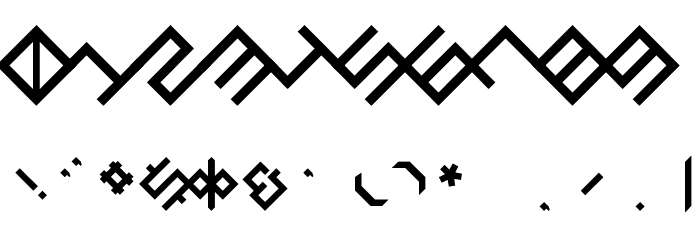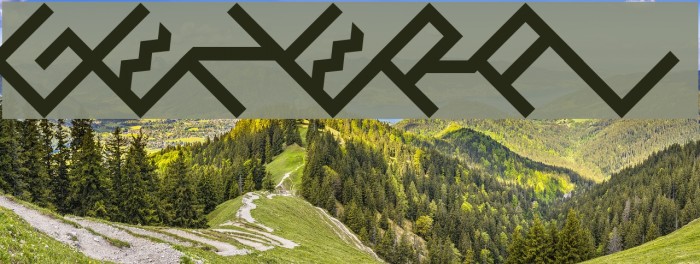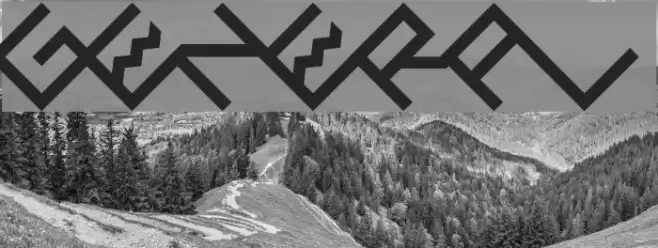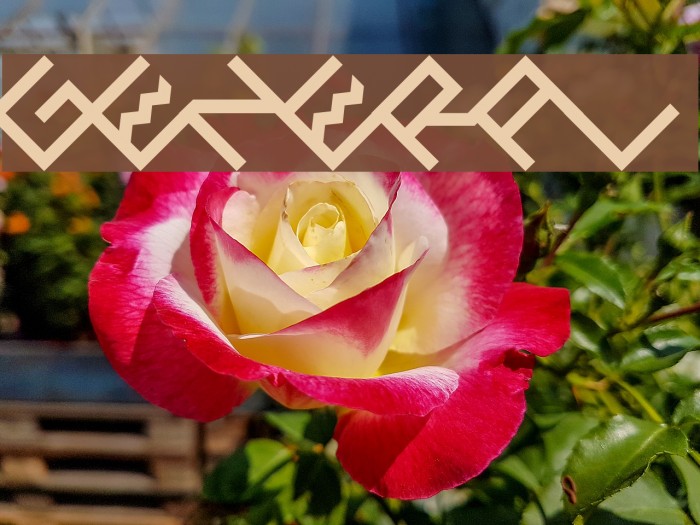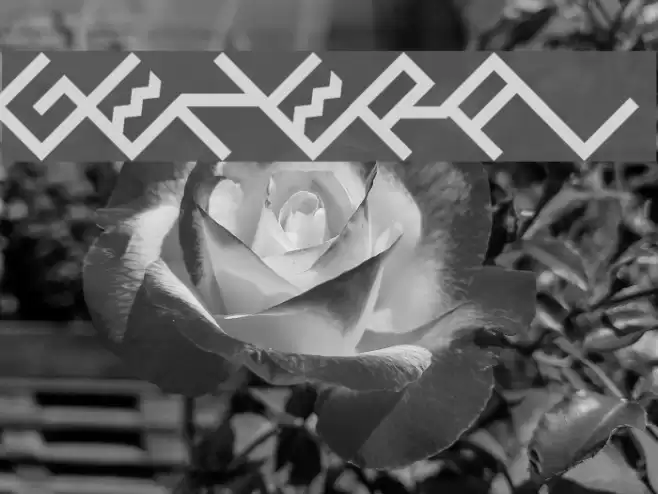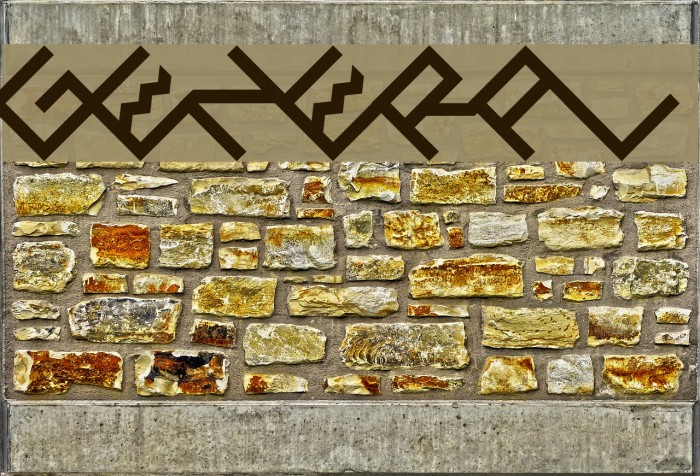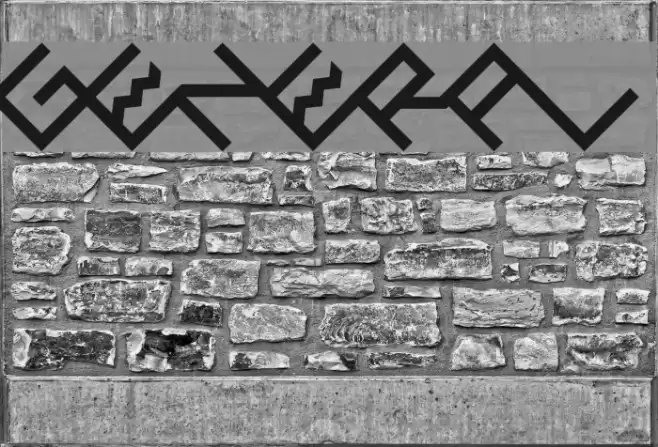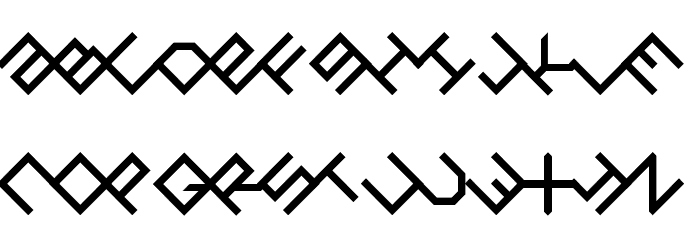
GENERAL Font
| Stile generale | Futuristic, Abstract |
| Caso d'uso | Logos, Posters, Titles |
| Progetti proposti | Ideal for sci-fi themed projects, modern art displays, or any creative work requiring a bold, abstract typeface. |